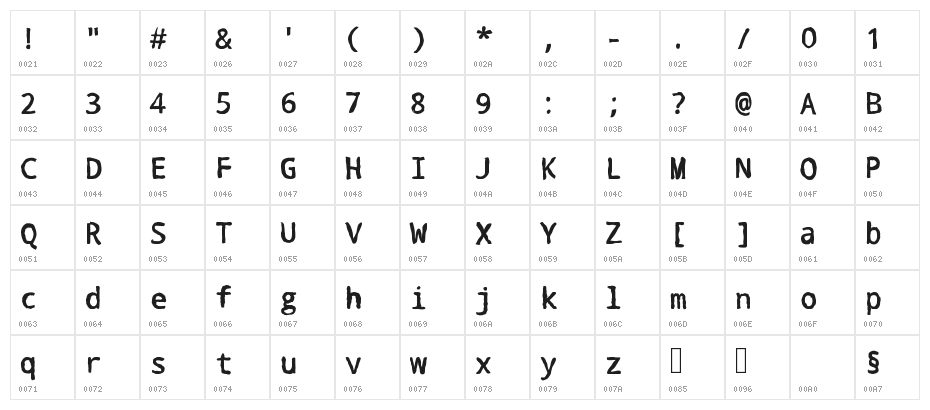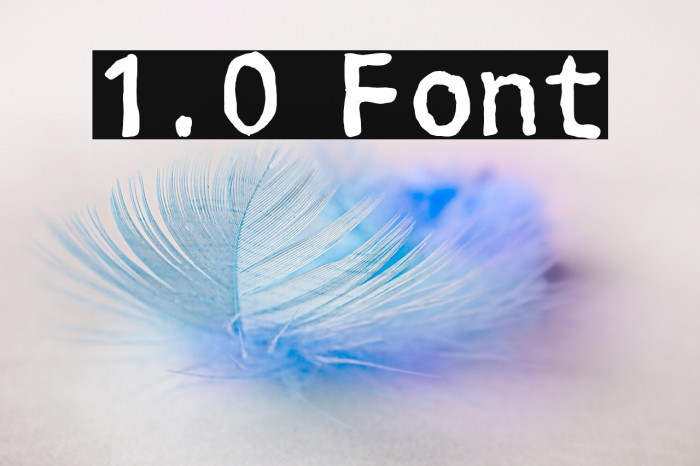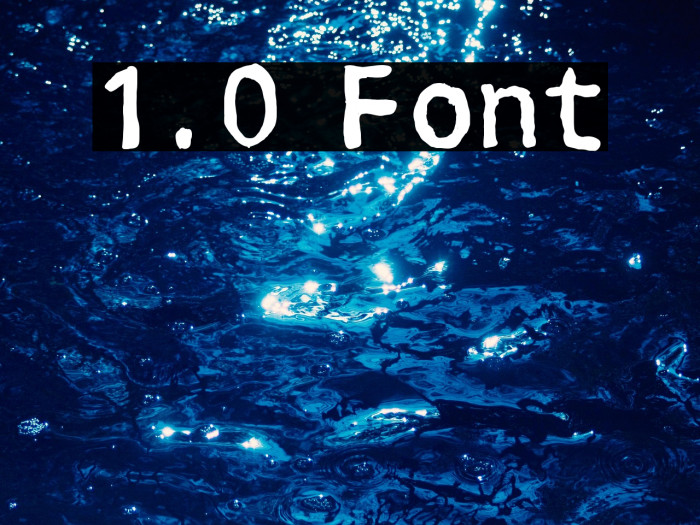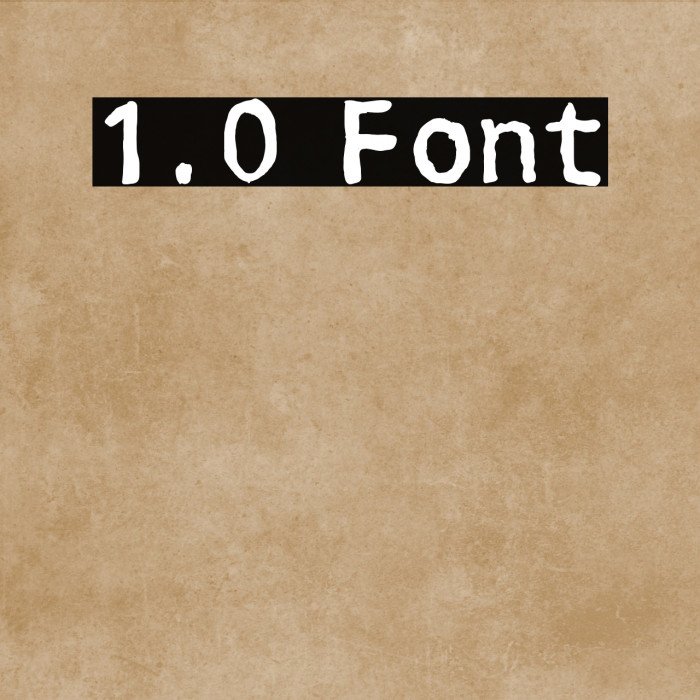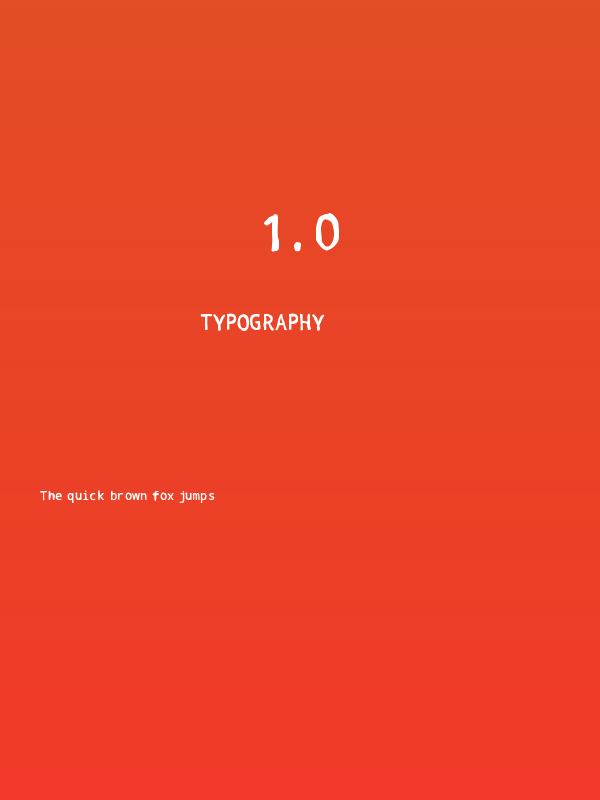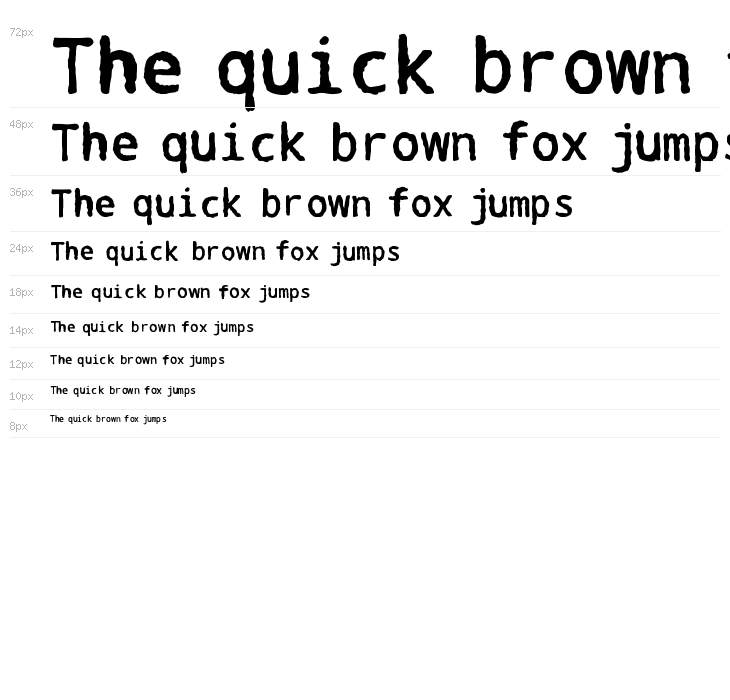
1.0 Font
| Stile generale | Casual, Playful |
| Caso d'uso | Headlines, Posters, Informal Text |
| Progetti proposti | Ideal for children's books, casual invitations, creative posters, and playful branding. |